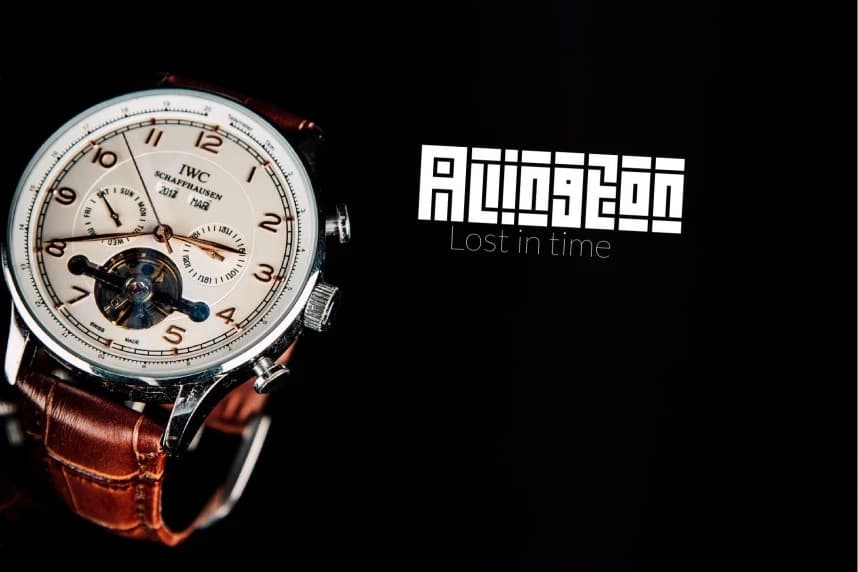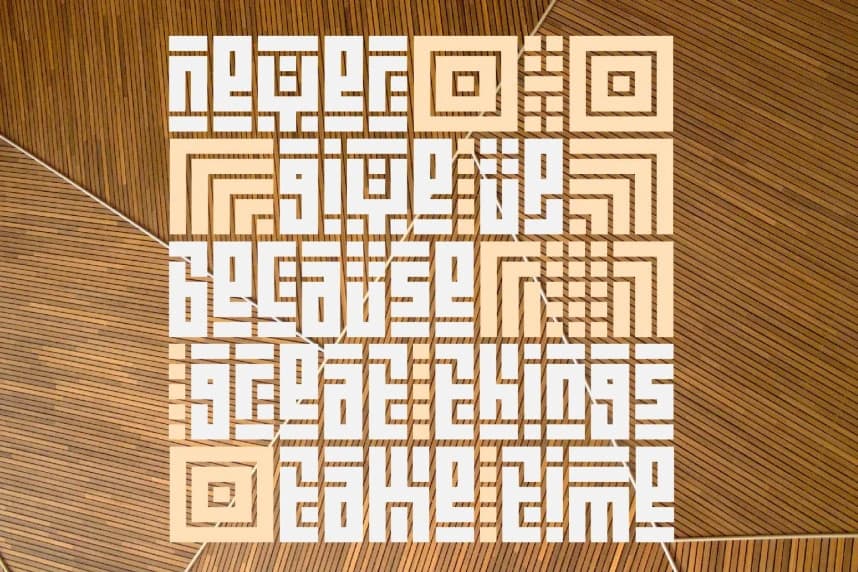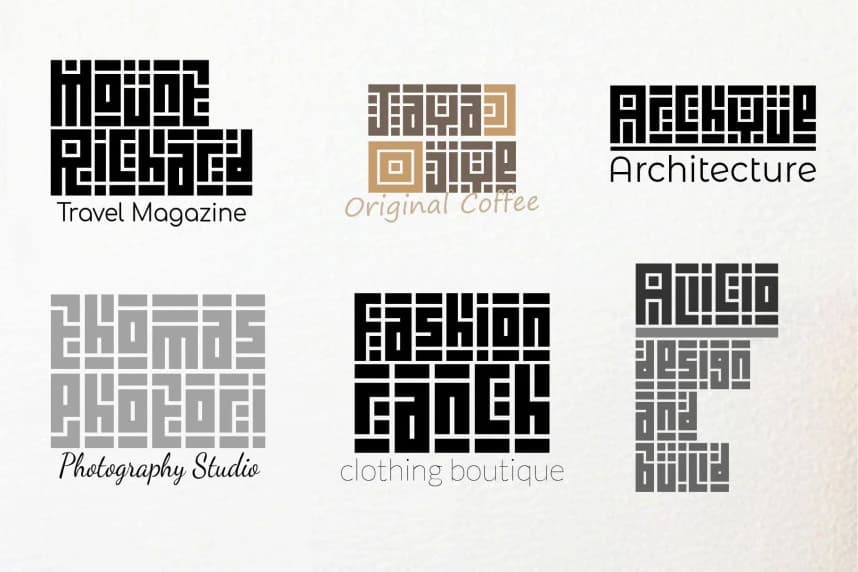
Kuficality Yazı Tipi
Kuficality Font, Arap kare hat kaligrafisinden esinlenen bir fonttur. İş ve kişisel kimlikler için logolarda harikadır. İşiniz için sadece birkaç saniyede benzersiz bir tasarım. Kuficality zarif ve klasik bir izlenim verir, ancak her harfin düz kare kesimiyle hâlâ modern görünüm sunar.
Kuficality Font, Arap kare kaligrafisinden ilham alınarak tasarlanmıştır. İş ve kişisel kimlik için logolar olarak harikadır. İşiniz için sadece birkaç saniyede benzersiz bir tasarım. Kuficality zarif ve klasik bir izlenim verir, ancak her harfin düz kare kesimiyle hâlâ modern görünümlüdür.